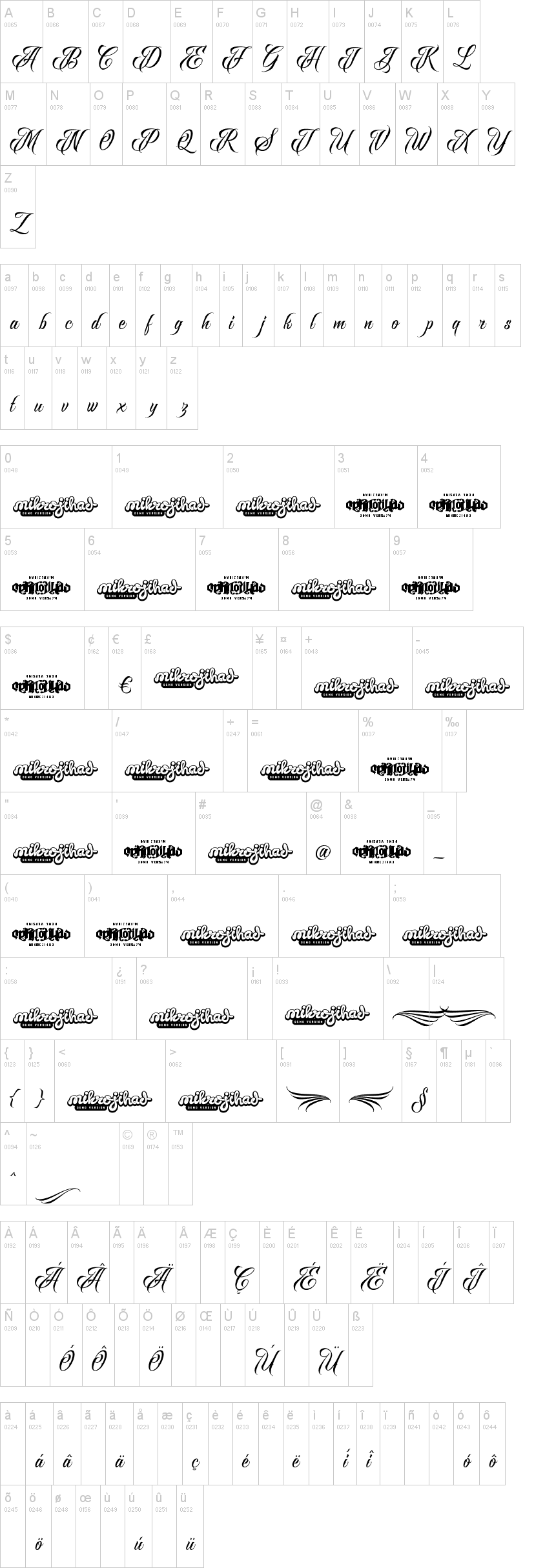
Raven Script 是一款精美的草书字体,由英国设计师 Paul Lloyd 创作。它具有流畅的曲线,优美的笔画,给人以优雅而又精致的感觉。它的特点是简练的笔画,节奏感强烈,让人印象深刻。它的字形设计既有传统古典风格,又有现代简约风格,是一款适合各种场合使用的字体。内容介绍
Raven Script是一款非常不错的手写艺术字体,具有很好的视觉感,适合于文化类的宣传设计、商业类品牌的广告和产品包装设计以及个性化文字排版等较多场景。